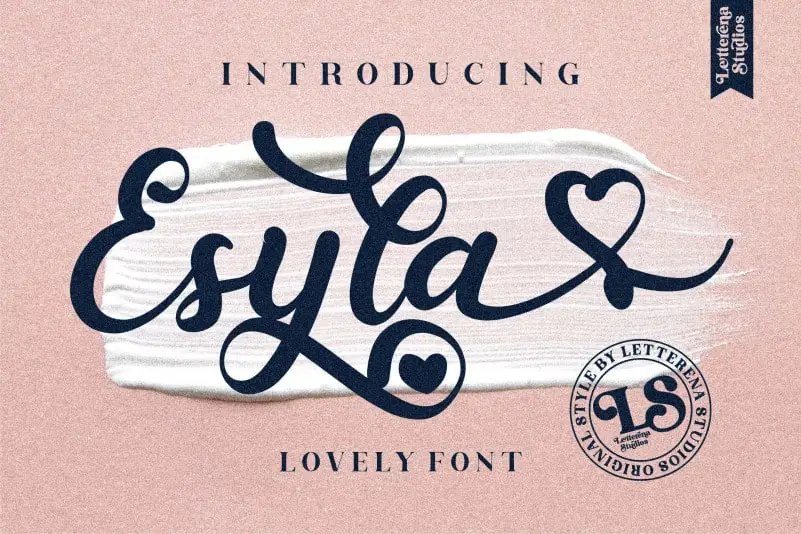
Esyla Script Font – Download Grátis
A Esyla Script Font é uma fonte script que traz a elegância do estilo cursive com um tom romântico e sofisticado. Este design bold não apenas torna cada carta de amor uma verdadeira obra-prima, mas também lhe dá o poder de transformar seus textos em algo único e inconfundível. PUA encoded, isso significa que você pode acessar facilmente todos os caracteres e círculos fantásticos desta fonte, proporcionando-lhe a liberdade para criar composições ainda mais belas. Especialmente indicada para designers apaixonados por trabalhos artísticos e amorosos, esta fonte é perfeita para projetos de arte, como cartões personalizados ou designs de site que exigem um toque romântico.